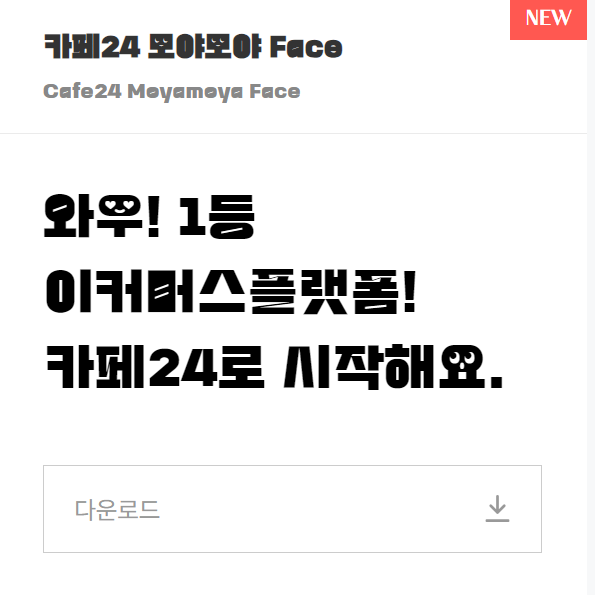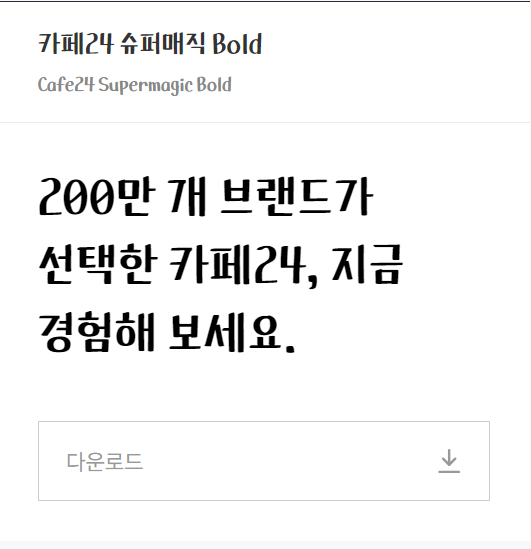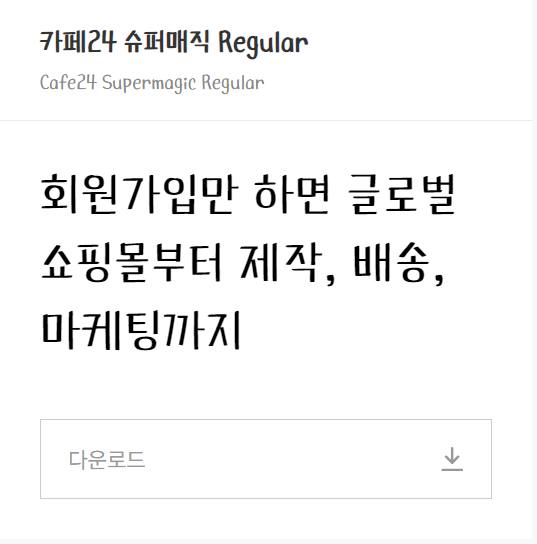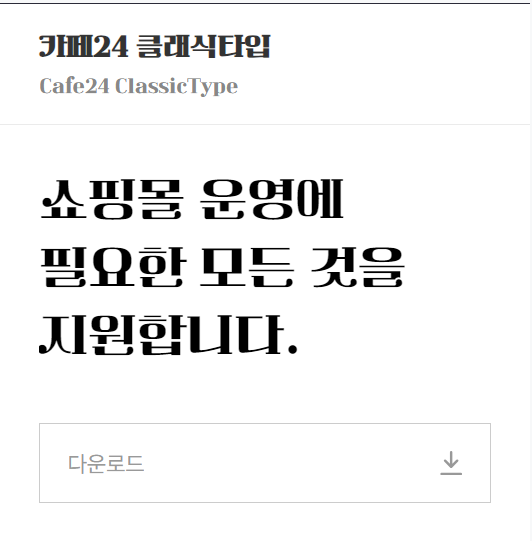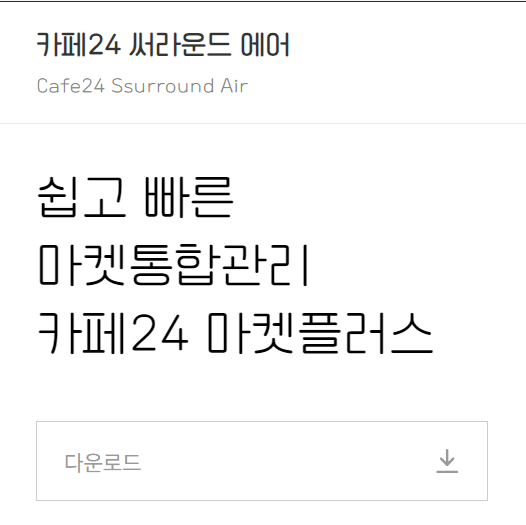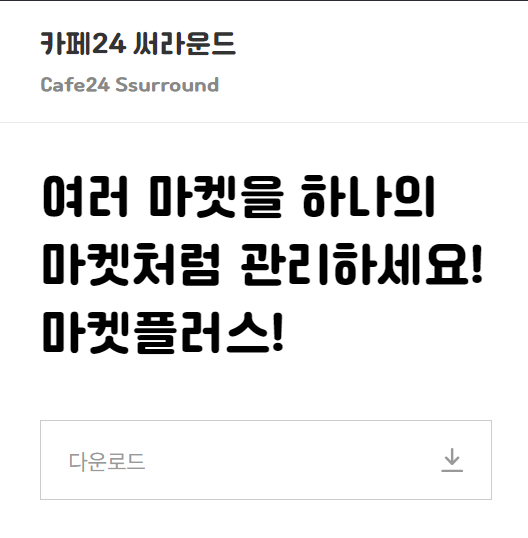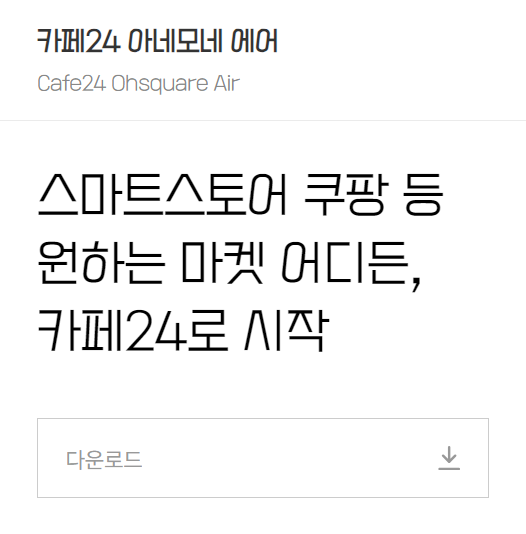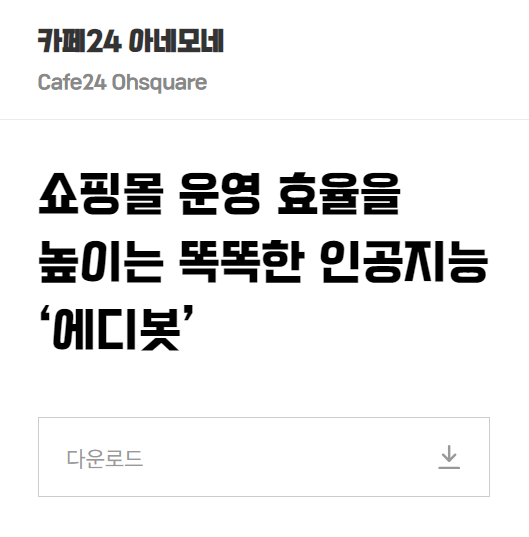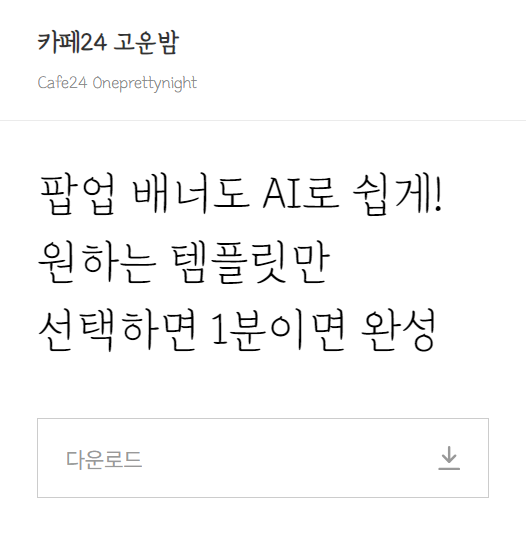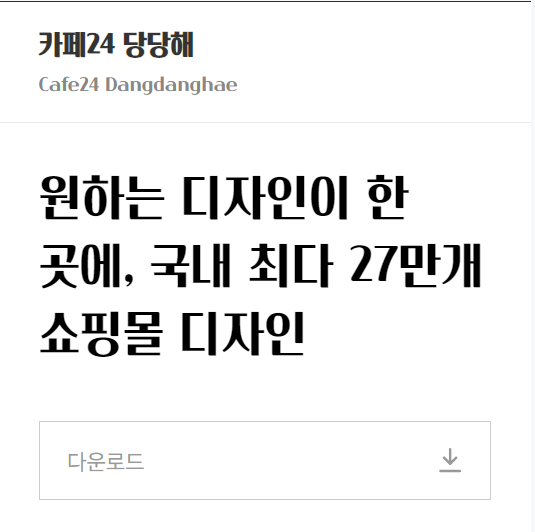
1. 모야모야 Face 무료 폰트
-귀여운 볼드체
-제목 및 강조 문구에 적합함
2. 슈퍼매직 Bold 무료 폰트
-얇은 볼드체
-곡선의 특징이 도드라짐
3. 슈퍼매직 Regular 무료 폰트
4. 클래식타입 무료 글씨체
5. 써라운드 에어 무료 글씨체
-스마트 스토어, 쿠팡 같은 상세페이지에서 자주 보는 글씨체
6. 써라운드 무료 폰트
-동글동글 귀여운 글씨체
-인스타툰에서 활용 가능
7. 아네모네 에어 무료 폰트
-무난한 글씨체
-제품을 판매하는 상세페이지 등에서 자주 볼 수 있다.
8. 아네모네 무료 글씨체
9. 고운밤 무료 폰트
10. 당당해 무료 폰트
-제목, 또는 중간 제목에 어울리는 글씨체
-가독성이 좋다.
11. 단정해 무료 글씨체
-우아하고 단정한 글씨체
-아늑한 느낌을 준다
12. 심플해 무료 폰트
-선이 가는 글씨체
-획 처리를 독특하게 꺾어서 흔해 보이지 않도록 만들었다.
13. 동동 글씨체 무료 다운
-인스타툰 등에서 활용가능한 글씨체
14. 쑥쑥 글씨체 무료 다운
15. 숑숑 글씨체 무료 다운
-끝선이 둥근 귀여운 글씨체